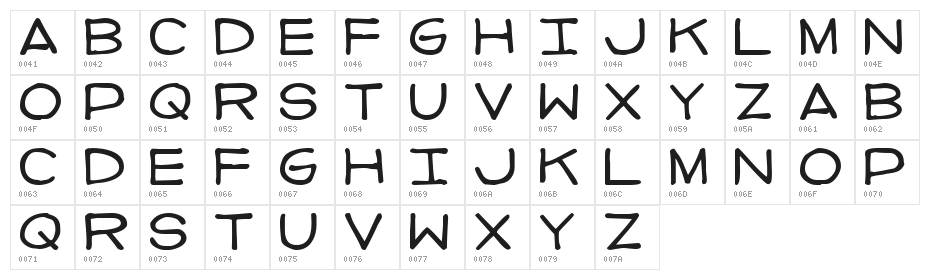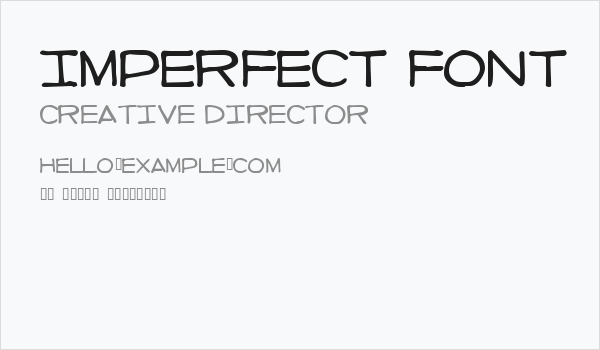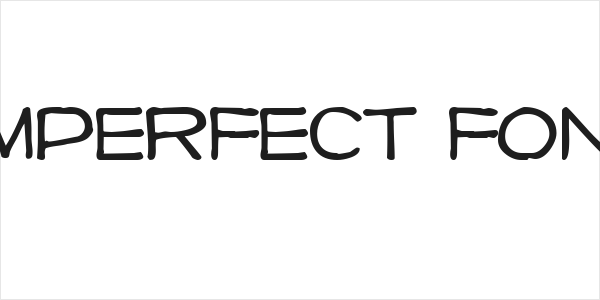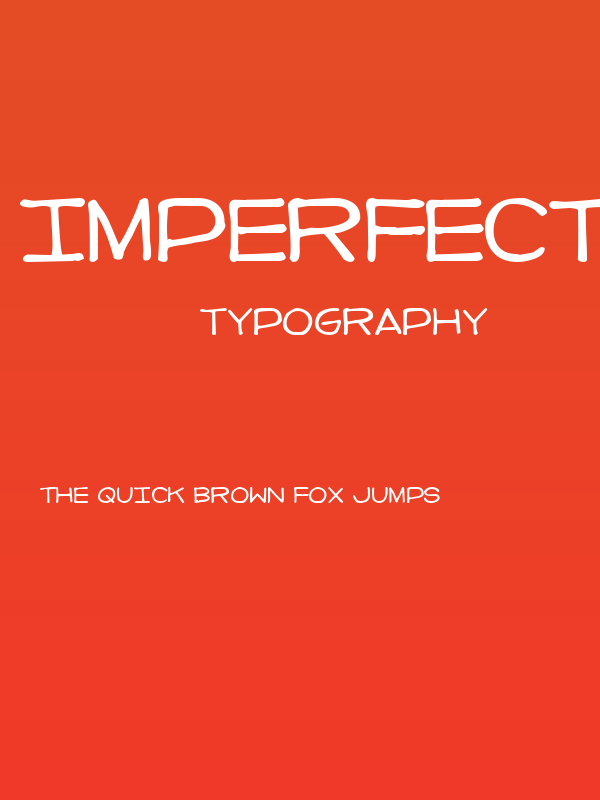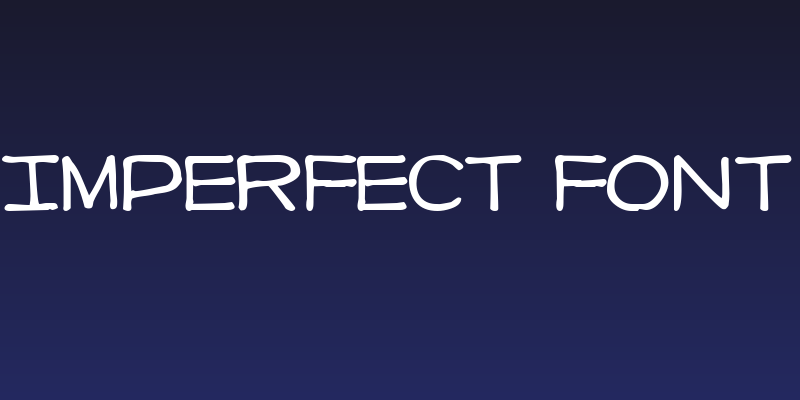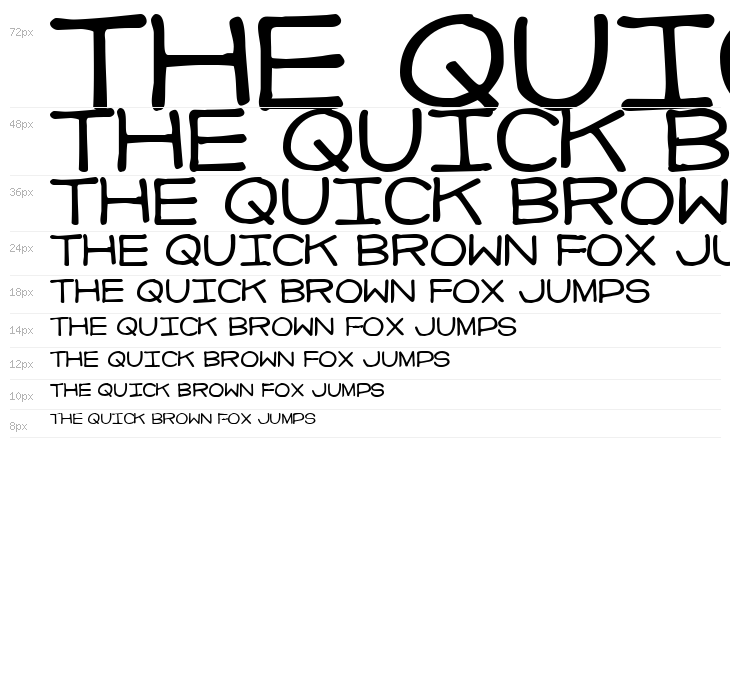
Imperfect font Font
| Stile generale | Casual |
| Caso d'uso | Headlines, Informal text, Branding |
| Progetti proposti | Ideal for children's books, greeting cards, casual branding, and playful social media graphics. |